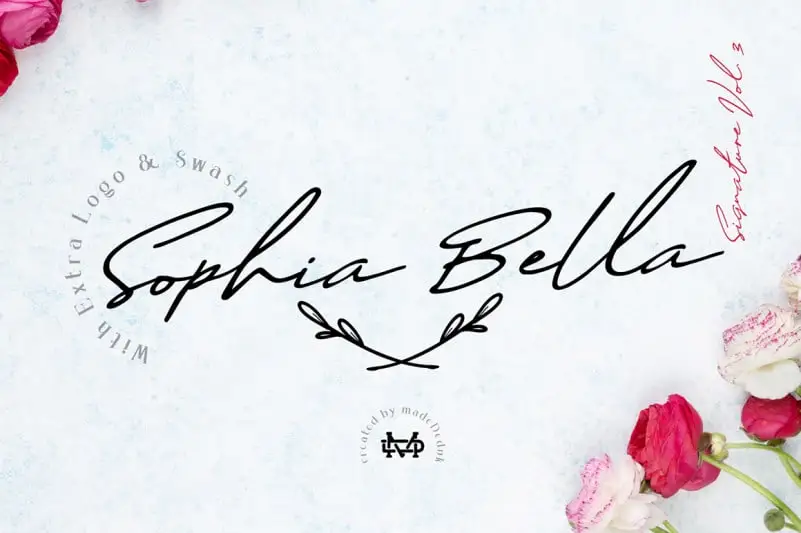
Sophia Bella Signature Font – Fonte Grátis
Sophia Bella Signature Font
Introduzimos a fonte ‘Sophia Bella Signature’. Esta é a terceira versão assinada e cuidadosamente criada à mão pelo designer madeDeduk, uma fonte de tipografia com mais de 170 ligações para tornar as letras aparentarem ser escritas livremente. Este design feito à mão traz um toque natural que vai dar ao seu trabalho um ar único e autêntico. A ‘Sophia Bella Signature’ é perfeita para uma variedade de projetos visuais, incluindo cartazes, capas de livros, produtos em geral, campanhas da moda, newsletters, marcas de marca, anúncios, revistas, encomendas de agradecimentos e capas de álbum, assim como criações para mensagens personalizadas. Sem dúvida, esta fonte irá adicionar uma textura única e um toque criativo ao seu design.